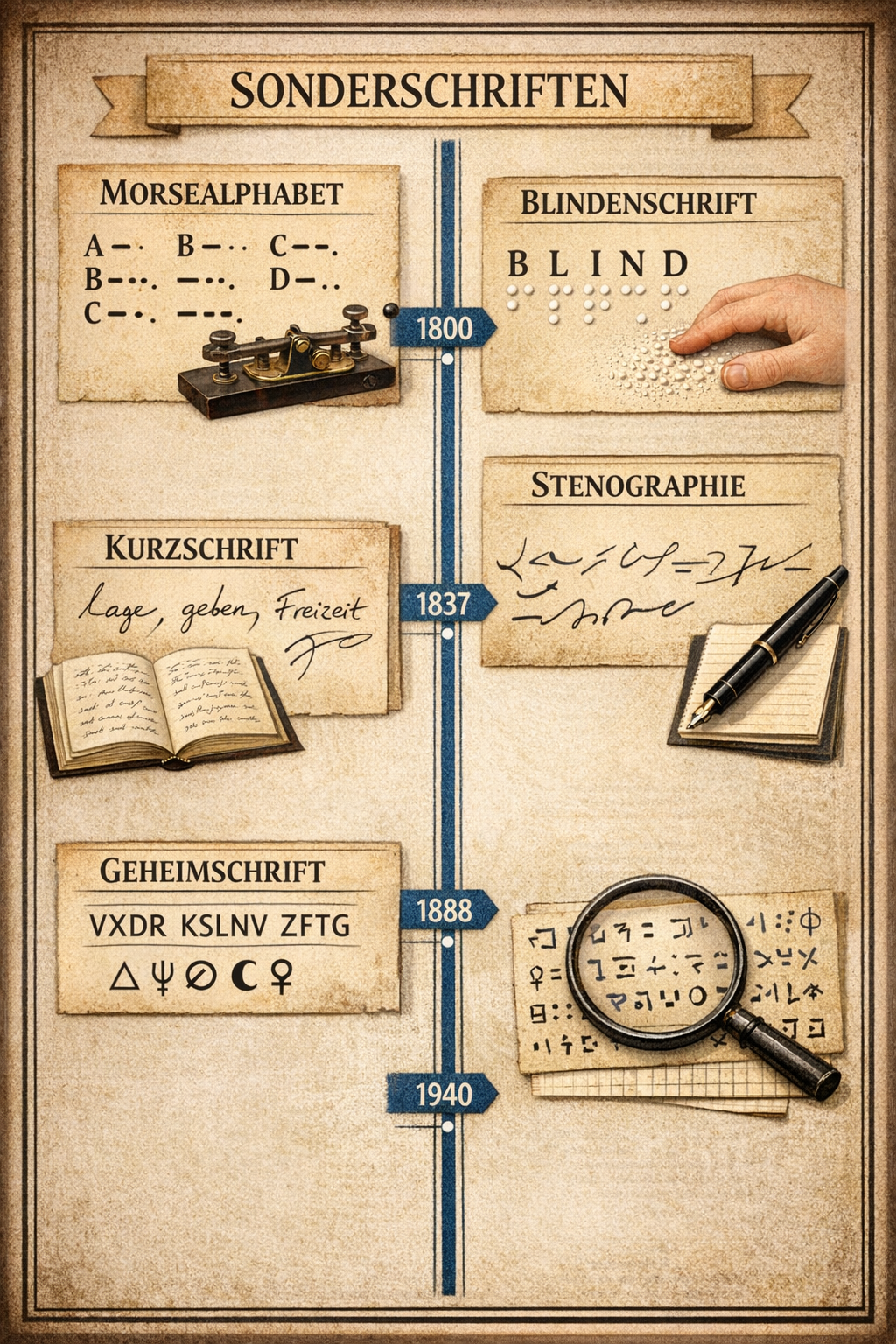
Wer auf besondere Weise schreiben muss — schnell, blind, über große Entfernungen oder geheim — braucht eine besondere Schrift. Stenografie, Braille, Morse und andere Sonderalphabete sind keine Schriften für den Alltag, aber sie zeigen, wie vielfältig menschliches Schreiben sein kann.
Steno, Morse & Co
Neben den großen Alphabeten gibt es Sonderschriften für besondere Zwecke: Stenografie für schnelles Mitschreiben, Brailleschrift für Sehende mit den Fingerspitzen, Morsecode für die Telegrafie — und mehr.
Schriften für besondere Zwecke
Sonderschriften im Überblick